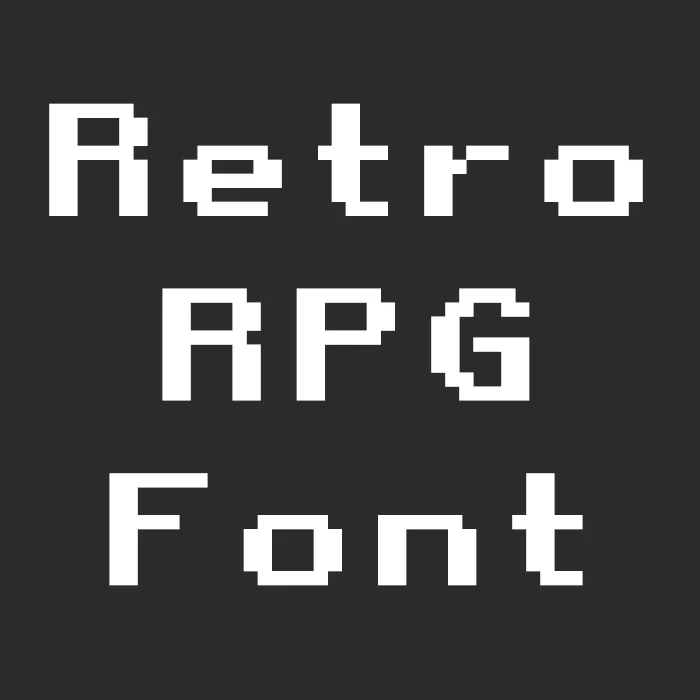
Retro RPG Font
Ресурспак Retro RPG Font добавляет в Майнкрафт стильный ретро-шрифт в духе классических RPG. Он отлично читается, подходит для ванильной игры и тематических сборок. Скачайте и окунитесь в ностальгию.
Retro RPG Font - это ресурспак, который меняет стандартный шрифт в Minecraft на стилизованный ретро-вариант в духе старых RPG-игр. Если вы фанат пиксельной эстетики и классических ролевых игр вроде Final Fantasy или Chrono Trigger, этот текстурпак для вас.
Что даёт Retro RPG Font
Обычный шрифт в Майнкрафт выглядит слишком современно и пресно. А здесь - приятный моноширинный шрифт с характерным ретро-стилем, при этом он остаётся легко читаемым. Не нужно щуриться, чтобы разобрать буквы - разработчик подошёл к делу с умом.
Изначально шрифт делался для сборки модов DarkRPG, но теперь его может скачать любой желающий. База - шрифт Retro Gaming Font от Daymarius, так что качество на высоте.
Зачем это нужно
• Ностальгия по старым RPG - идеально для сборок в жанре
• Улучшает атмосферу без потери читаемости
• Работает как замена скучному ванильному шрифту
• Подходит для серверов с RPG-тематикой